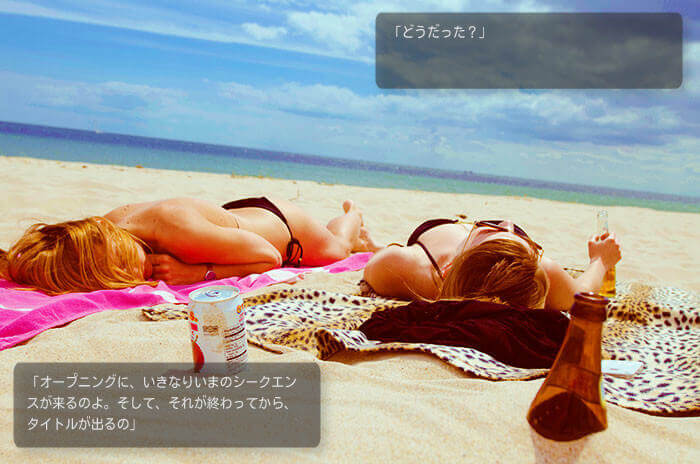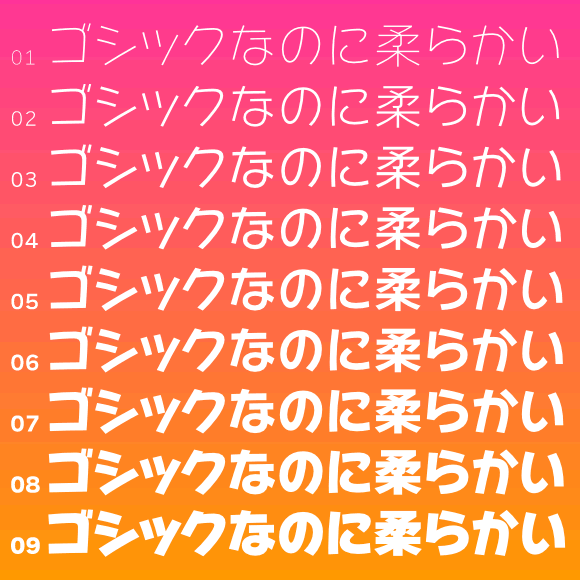
日本語も対応!等幅フォント28個まとめ
文字によらずすべてが同じ幅に揃っているフォントを等幅フォントと言います。等幅フォントを使用すると同じ文字数であれば行の最後も揃うことができます。プログラミングをする時などにおススメのフォントです。
MTたれ
落書き調のユニークな等幅フォント。
NasuM
見た目が似ていてまちがいやすい文字・見た目が同じだが違う文字を、判別しやすくするフォント。
NatuMono
源真ゴシック (げんしんゴシック)の等幅 Regularを改変したフォント。
S2Gうにフォント
手書き文字から作成された等幅フォント。
S2Gうみフォント
手書き文字から作成されたフォント。手紙などに使用するとかわいらしい印象を与える。
S2Gつきフォント
手書き文字から作成された細めで可愛いい等幅フォント。
S2Gメモ
「メモ書き風味」の等幅フォント。
S2Gらぶ
ハートがデザインされているかわいい日本語フリーフォント。
S2G殴り書き
手書き文字から作成された等幅フォント。
S2G海フォント
手書き文字から作成された等幅フォント。
S2G月フォント
手書き文字から作成された等幅フォント。
Uemaruフォント
濁点・半濁点を文字の上に付けたTrueTypeアウトラインフォント。
VL ゴシック
M+ アウトラインフォントベースのモダンゴシック体の日本語 TrueType フォント。
あずきフォント
「マジメすぎず、可愛すぎない」をイメージした手書きフォント。
あずきフォントB
上記の「あずきフォント」の太字版。
アニトL-等幅教漢
シンプルでクセのない、素直なデザインの丸ゴシック書体。等幅フォントバージョン。